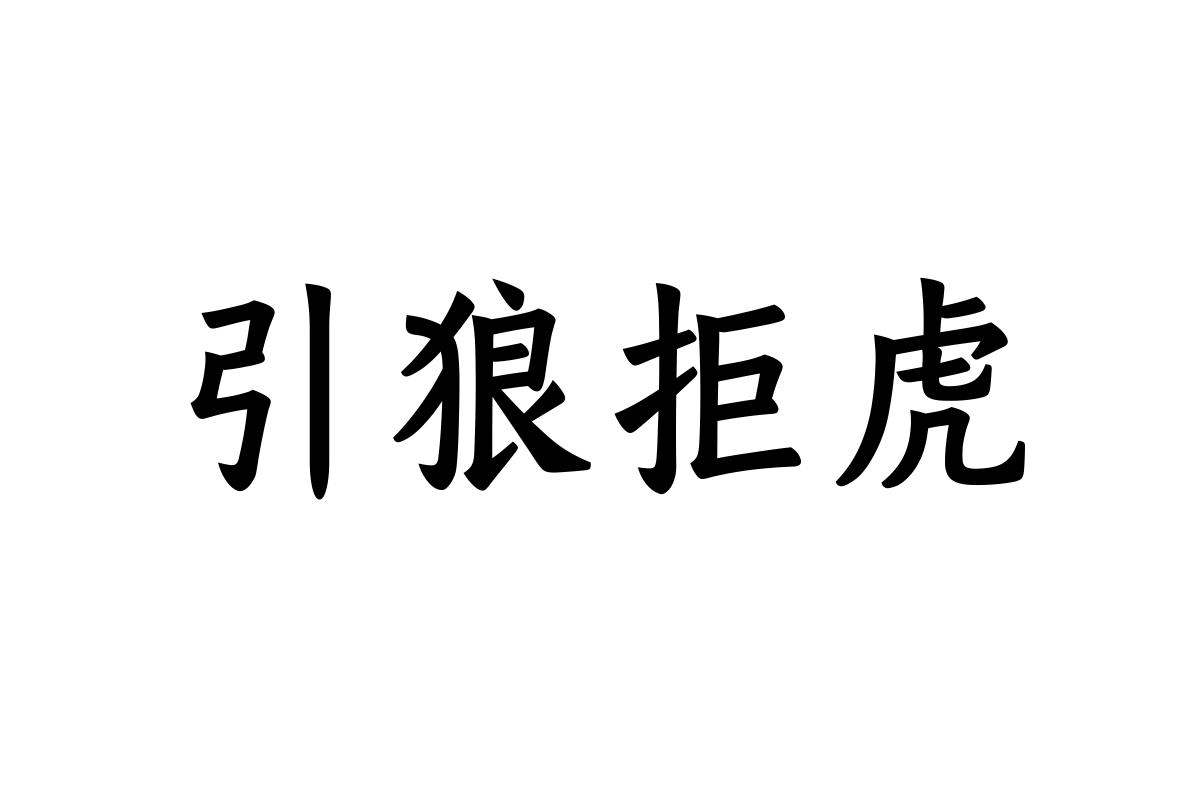
汉仪楷体是一款经典的中文字体,具有清晰易读、美观大方的特点。这款字体适用于各种印刷品和电子文档,如报纸、杂志、书籍、广告牌等。它的笔画流畅,结构紧凑,给人一种简洁而有力的感觉。汉仪楷体在设计上注重细节,每个字的笔画都经过精心设计,使得整体呈现出一种和谐统一的效果。此外,汉仪楷体还具有较高的可读性,无论是在印刷还是电子显示中都能保持清晰可见。总的来说,汉仪楷体是一款非常适合用于正式文件和商业宣传的字体。